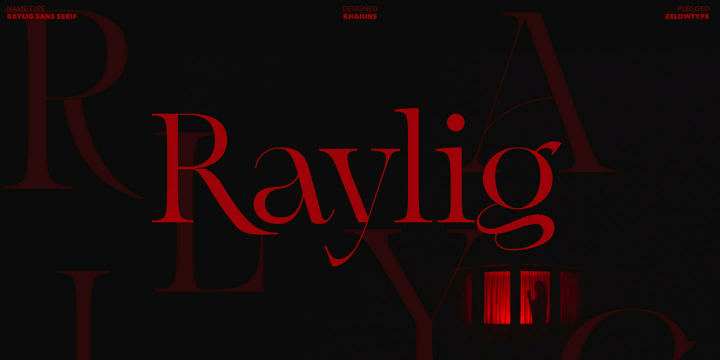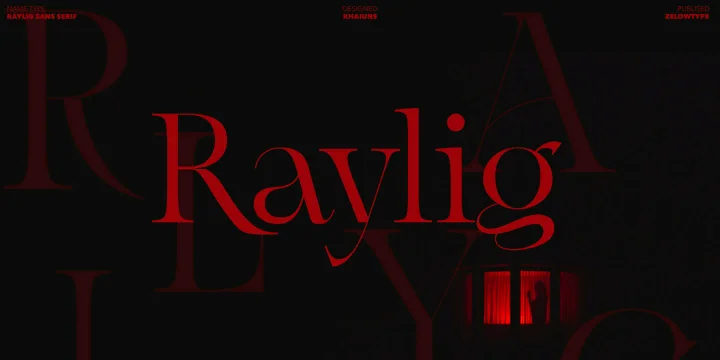
Название: Raylig Font (2021)
Raylig - это изящная засечка, но полная энергии, Raylig - это экспериментальный проект, полный эгоизма в нем, этот проект был разработан khaiuns в мае 2021 года, он сделал его сам, так что это заняло около 4 месяцев.
Raylig - это желание представить идеальный шрифт для ваших разнообразных проектов, чтобы этот тип шрифта можно было выбрать для брендинга, особенно в индустрии UI / UX, также подходит для типографической верстки для журналов, плакатов, книг и т.д.